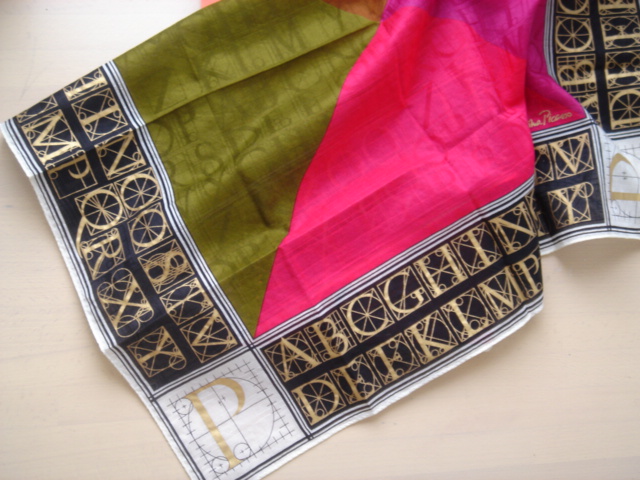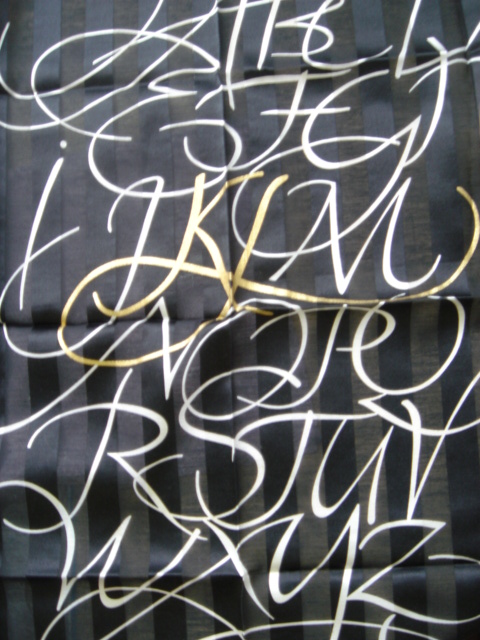
アルファベットのハンカチーフ
おしゃれな人からの贈り物…刺繍の美しいハンカチです。
とっても薄い綿ローン地に繊細な手刺繍で、葉っぱのところは裏側に糸がわたっているので表面はぷっくりと見える…アップリケをしたみたいな。
一枚の布として見ても、ハンカチって魅力的ですよね。
最近こんな優美なハンカチを使うことが少なくなりました。手を拭くのにはタオル素材のハンカチを使っているためです。
タオルハンカチはそれなりにかわいく、しかも実用的。だけど、日々美しいものを身の回りに置いて、見たり、使ったりも大事ですよねえ。
涙をそっと押さえたり、とか?美女なら持っているだけで
絵になります。
さて、文字入りのハンカチは引き出しにあったはず…ありました〜
華やか!周囲全部ローマンキャピタルですから!プロポーションをしっかりお勉強、って感じですかね。
パロマ・ピカソの名前入ってる…あ、だから四隅は「P」なのね。
中央の地模様も全部アルファベット。ごちそうさま〜
こういうハンカチってデザイナー本人がデザインしているのでしょうか?
絹と綿が半々のスベスベの手ざわり。周りの切り文字っぽいデザインがおもしろい。
中央部分の字はあまり好きではないけれど…「KとL」が金色になっているのは、カール・ラガーフェルドだから、か。イニシャルが隣り同士というのは、こんなふうに遊べるのですね、いいなあ。
久しぶりに出してみて思ったこと。もったいなくて使えない、よりも使って楽しいほうがいいかも。